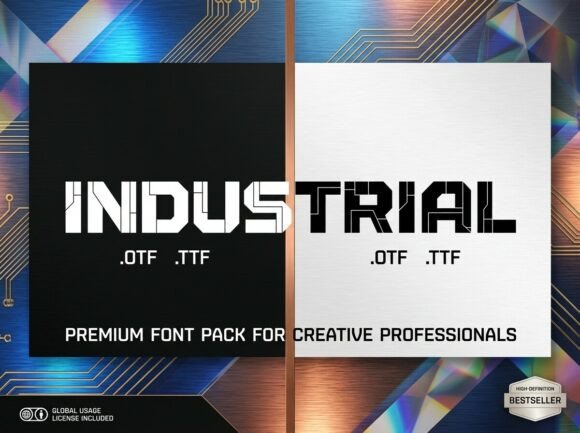
Industrial
Industrial์™€ ๊ฐ™์€ ๊ณ ํ’ˆ์งˆ ์ž์‚ฐ์„ ์ฐพ๊ณ  ์žˆ๋‹ค๋ฉด ์ด ํ”„๋ฆฌ๋ฏธ์—„ ํŒจํ‚ค์ง€๋Š” ์ฐฝ์˜์ ์ธ ํ”„๋กœ์ ํŠธ๋ฅผ ์œ„ํ•œ ํ™˜์ƒ์ ์ธ ์„ ํƒ์ž…๋‹ˆ๋‹ค.
POD(์ฃผ๋ฌธํ˜• ์ธ์‡„) ์ œํ’ˆ, ๊ฒฐํ˜ผ์‹ ์ดˆ๋Œ€์žฅ ๋˜๋Š” ์†Œ์…œ ๋ฏธ๋””์–ด ๊ทธ๋ž˜ํ”ฝ์„ ๋งŒ๋“ค ๋•Œ Industrial๋Š” ์ด์ƒ์ ์ธ ์„ ํƒ์ž…๋‹ˆ๋‹ค.